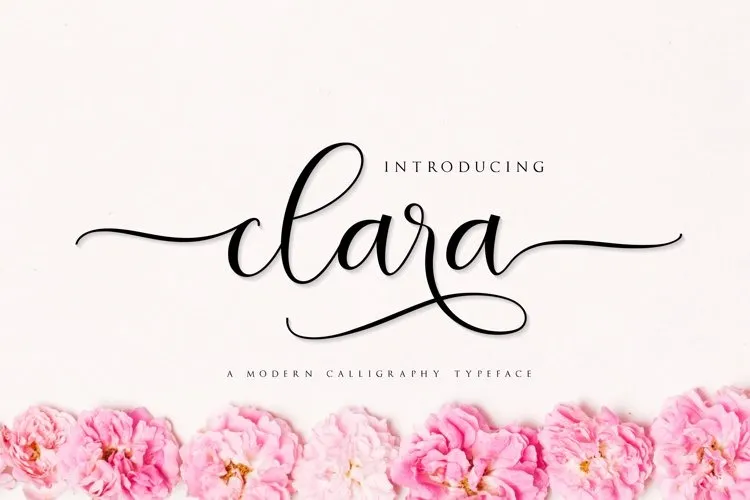
A Clara Font é uma tipografia criada através do processo de escrita a mão que traz formas únicas e modernas do calligrafia. Sua escrita tem uma naturalidade impressionante, evocando um estilo autêntico e verdadeiro. Esta fonte proporciona um toque sofisticado em diversos projetos, como logomarcas e identidades, convites de aniversário ou embalagens personalizadas, designs para casamentos, posts nas redes sociais, anúncios, embalagens de produtos, etiquetas, fotografias e até mesmo em eventos especiais. Ela é perfeita para adicionar um toque único e autêntico a qualquer projeto visual. Composta por uma ampla variedade de itálicos e fontes, a Clara Font oferece-lhe o que você precisa para transformar seus ideais em realidade, deixando sua marca mais forte e atraente.